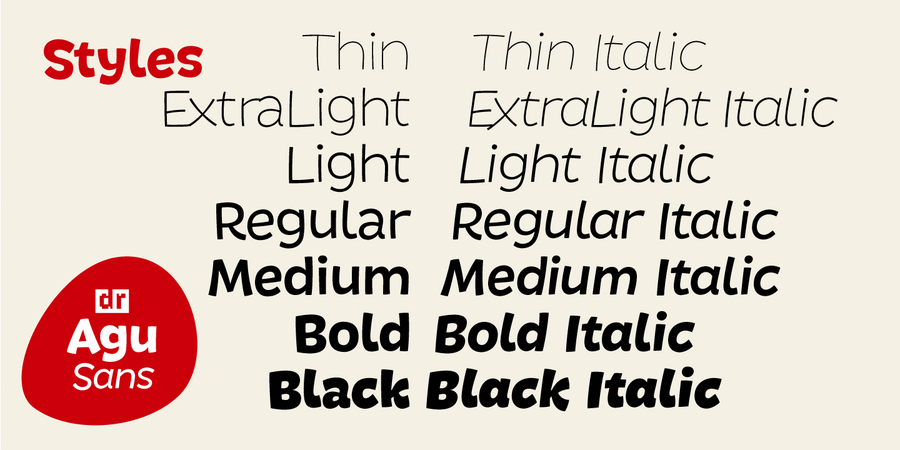
Опис гарнітури DR Agu SansАгу Санс – это шрифтовое семейство с набором прямых и курсивных начертаний от сверхсветлого до сверхжирного. Может применяться для неформальных текстов, детских книжек и приложений. Шрифт разработал Дмитрий Растворцев в 2012 году.
Асоціації з сімейством шрифтів DR Agu SansОсобистість і характер гарнітури:
веселий, задерикуватий, смішний, доброзичливий, добродушний, добрий, радісний, стрибучий, неохайний, грайливий, привітний, пустотливий, непосидючий, рухливий, оригінальний, свіжий, тонкий, легкий, дитячий, наївний, невагомий, прозорий, ніжний, повітряний, дротяний, динамічний, худий, щасливий, літній, карикатурний, милий, мультяшний, дотепний, домашній, симпатичний, стиглий, смачний, важкий, помітний, яскравий, новорічний, активний
дитяча книжка, канцтовари, олівці, зошит, анімація, мультфільм, графіка, ілюстрація, школяр, ранок, гумор, селфі, Інстаграм, школа, табір, сніданок, іграшка, їжа, гра, учень, дитяче харчування, зоопарк, клоун, зоомагазин, тварини, відпочинок, щоденник, цирк, дім, закуска, розфарбування, піцца, базар, десерт, морозиво, Новий рік, дитсадок, дитячий ранок, Christmas Гарнітура асоціюється з віком: